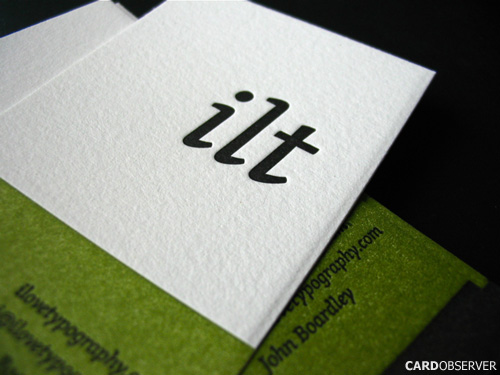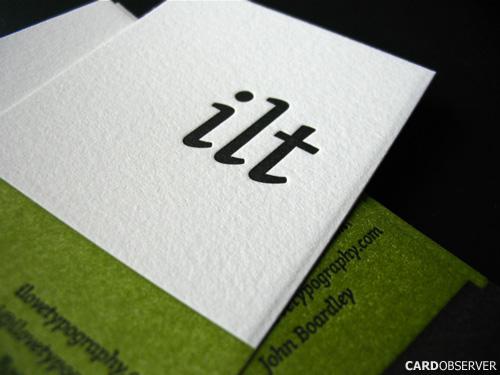
Bin gespannt auf eure Ideen
ich bin zufällig auf diese Visitenkarte gestoßen, vielleicht kennt ihr sie schon, ist ja recht Themenverwandt.
Habt ihr eine Vermutung welche Schriftart es sein könnte?
Wow, eine wunderschöne Schrift.